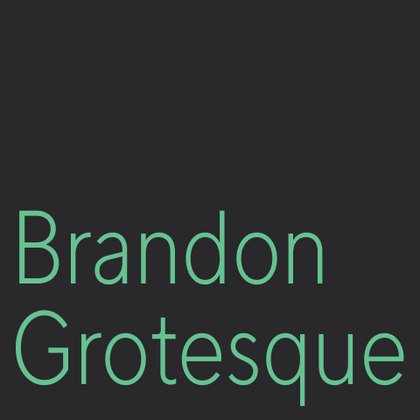
Шрифты похожие на Brandon Grotesque
Если вам нужна гарнитура с дружелюбной геометрией, как шрифт Brandon Grotesque, обратите внимание на коллекцию TypeType. Гарнитуры TypeType добавят индивидуальности вашему проекту. Альтернативные шрифты — лучший выбор для брендинга, веб-дизайна, рекламных кампаний, упаковки и презентаций.
Если вы устали от «заезженных» шрифтов и ищете гарнитуры, похожие на Brandon Grotesque, ознакомьтесь с нашими лучшими альтернативами Brandon Grotesque. Это шрифты, которые имеют близкие характеристики, но в то же время обладают новыми уникальными особенностями дизайна. Например, относятся к той же категории шрифтов, подходят для тех же целей и имеют похожие черты, но отличаются в деталях или пропорциях.
В TypeType вы найдете передовые шрифты, такие как Brandon Grotesque и даже лучше: вот несколько замечательных и не столь распространенных альтернатив Brandon Grotesque. Используйте этот список высококачественных, выглядящих как Brandon Grotesque шрифтов, на свой вкус. Так вы сможете подобрать еще более для вашего проекта подходящий шрифт, расширив выбор, или освежить свой дизайн. Все шрифты, представленные в этой коллекции, доступны в разных форматах и по доступным ценам, поэтому вы сможете найти тот, который соответствует любым потребностям!
Найдите отличную замену Brandon Grotesque и попытайтесь имитировать похожее настроение, передать нужное вам ощущение, используя его в своих проектах. Каждый шрифт, представленный на этой странице, является двойником шрифта Brandon Grotesque, фактически его полным аналогом.
TT Commons™ Classic — универсальный геометрический гротеск для широкого круга задач.
TT Interphases Pro — неогротеск, который создавался специально для работы в интерфейсах. Среди визуальных особенностей TT Interphases Pro — плавные формы скруглений, повторяющиеся во всех элементах: благодаря им большие массивы текста читаются легко и приятно.
TT Gertika — геометрический гротеск с динамичным характером и танцующим ритмом. Идея шрифта зародилась из леттеринга на американском плакате второй половины 30-х годов.
TT Travels Text — геометрический гротеск с широкими пропорциями. Основные визуальные отличия TT Travels Text — достаточно широкие пропорции и немного сквадраченные формы овалов.
TT Firs Text создавался на основе обновленной в 2023 году гарнитуры TT Firs Neue. Мы сохранили эстетику скандинавского минимализма, но полностью перерисовали все выразительные элементы, сделав их более мягкими и традиционными.
TT Lakes Neue в версии 2.0 — продолжение геометрического гротеска, вдохновлённого финским функционализмом. Новая версия предоставляет больше возможностей, ведь мы не только увеличили кассовый состав и улучшили шрифт технически, но и доработали его визуальный характер.
TT Rounds Neue — гротеск со скругленными формами. В тонких начертаниях шрифт выглядит довольно минималистично и нейтрально: скругленные окончания штрихов становятся практически незаметными, на первый план выходят плавные линии.
TT Norms Std Condensed является логическим развитием нашего бестселлера TT Norms Pro. Несмотря на то, что шрифт обладает более узкими пропорциями относительно исходной гарнитуры, он унаследовал классические пропорции знаков, внимание к деталям и дотошную проработку каждого знака в шрифте.